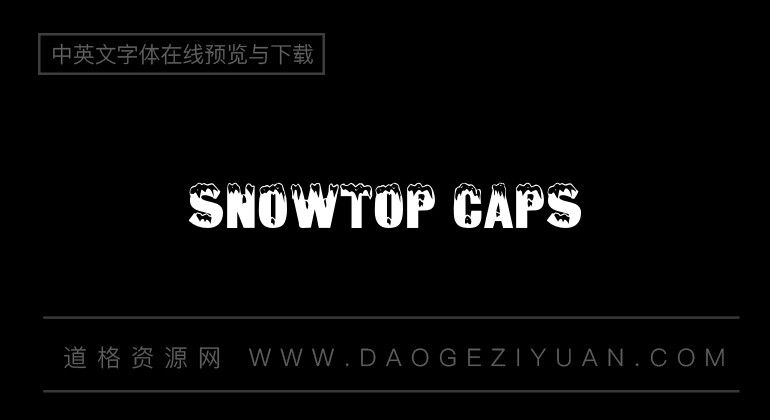
Snowtop Caps
Snowtop Caps 是一种装饰性字体,其特点是每个字母都被设计成类似于积雪覆盖的样子。这种字体看起来非常有趣,适合用于寒冷季节的设计主题,例如圣诞节、冬季或者冰雪主题的海报、广告、贺卡或其他印刷品上。 Snowtop Caps 字体由字母、数字和一些标点符号组成,其中每个字母都高大上,并且都有一些小的装饰元素,例如点、线和花纹。这些元素使得每个字母都看起来像是被雪花覆盖了一样,因此给人一种温暖、舒适、神秘和神圣的感觉。 总的来说,Snowtop Caps 字体是一种非常有趣、富有创意和高度装饰性的字体,能够让设计师在节日和寒冷主题的设计工作中大放异彩。
Snowtop Caps是一款非常不错的手写艺术字体,具有很好的视觉感,适合于文化类的宣传设计、商业类品牌的广告和产品包装设计以及个性化文字排版等较多场景。